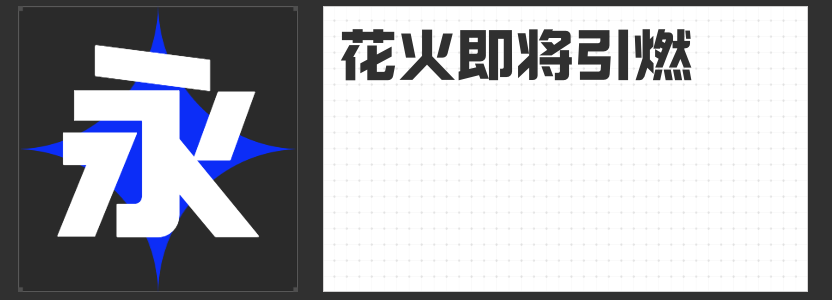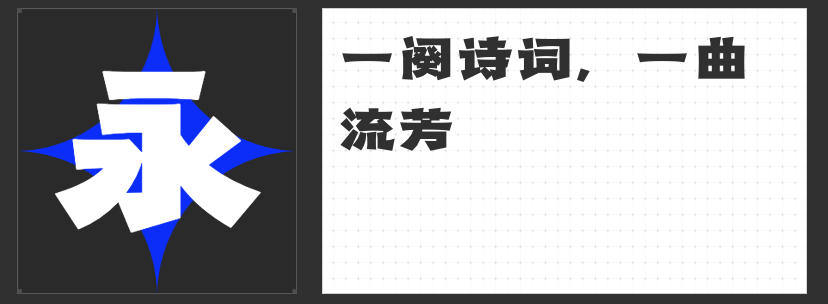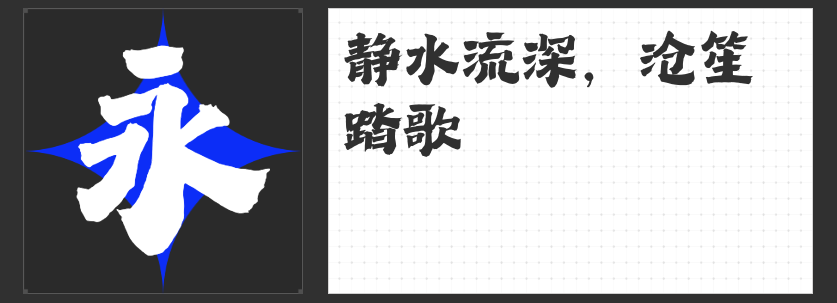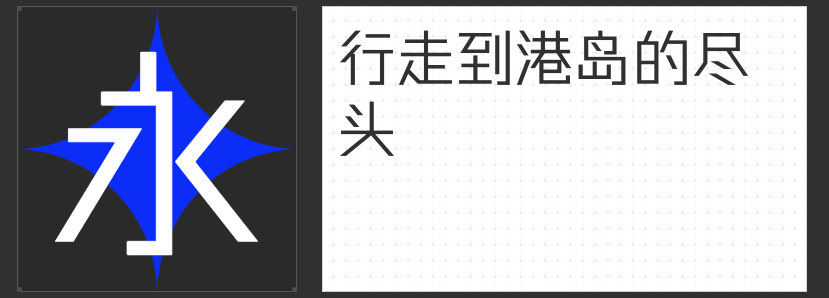
博物馆文创字体精选:让文化之美跃然纸上
在博物馆的文创天地里,字体不仅是文字的载体,更是文化的传承者与创新者。今天,我们精心挑选了四款独具魅力的字体,它们将如何为博物馆文创产品增添无限风采,让我们一同探索。
1.造字侠热辣隶简
这款字体融合了传统隶书的古朴韵味与现代设计的简约风格,其独特的字形和线条,仿佛能瞬间将观众带入那个遥远而辉煌的历史时代。它非常适合用于制作复古风格的文创产品,如书签、笔记本封面或是文化衍生品包装,让每一次翻阅都仿佛在与古人对话,感受那份跨越时空的文化共鸣。
这款字体以其粗犷有力的笔触和坚定的气质,传递出积极向上的力量。在博物馆文创产品中,它可以被应用于励志主题的笔记本、徽章、T恤等,鼓励人们勇敢面对生活的挑战,不断追求梦想与进步。
这款字体带有浓厚的都市气息和独特的香港风情,其硬朗的线条和简洁的设计,非常适合用于展现现代都市风貌的文创产品,如城市风光画册、旅行纪念品等。它能让观众在欣赏文创产品的同时,感受到香港这座城市的独特魅力和文化底蕴。
4.万人字造踏歌行体
这款字体以其流畅而富有动感的线条,让人联想到古代文人墨客的行吟与歌唱。在博物馆文创产品中,它适用于诗词歌赋、书法卷轴、文化衫等,能够生动展现中华文化的博大精深和独特韵味,让观众在品味文化的同时,也能感受到那份来自心灵深处的共鸣与感动。
总之,这四款字体各具特色,无论是复古、励志、都市还是文化韵味,都能为博物馆文创产品增添独特的魅力和价值。让我们一同期待这些字体在文创产品中的精彩呈现,共同感受文化的力量与美好。